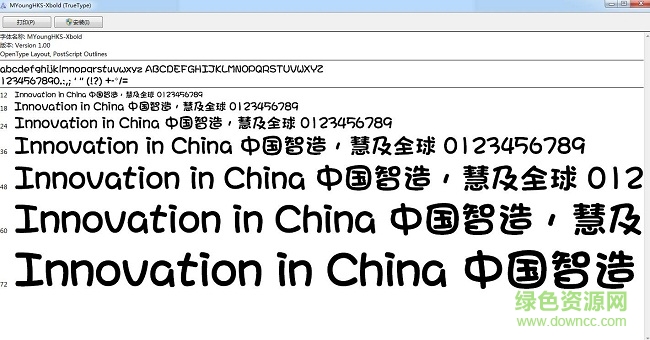
myounghks-xbold-粗體字體又叫蒙納簡粗俏皮體,是一款十分可愛的卡通字體,俏皮活潑適合歡快有趣的廣告主題設(shè)計,應(yīng)用效果很特別,感興趣的朋友快來下載吧!
一般在表現(xiàn)愛情、柔美、女性、兒童等主題上比較常用,如華康少女體、華康娃娃體以及漢儀小麥體都是用的比較多的可愛卡通型中文字體。